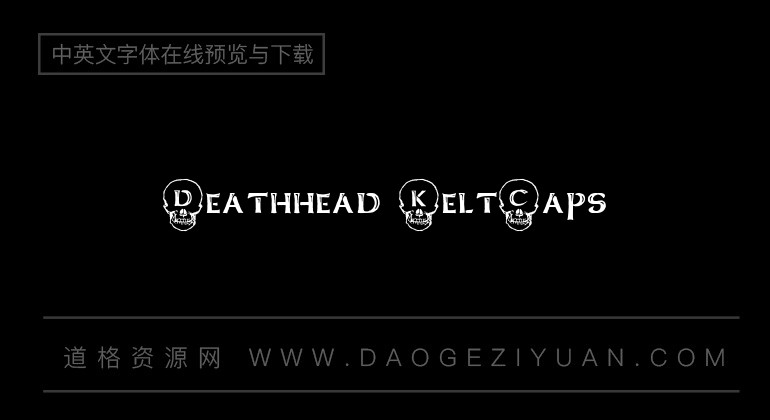
Deathhead KeltCaps
Deathhead KeltCaps 字体是一种基于凯尔特文化元素的装饰性字体。这种字体的特点是字母的轮廓线条粗细不均,有些字母的上方会有尖锐的尖刺,字母之间也存在一定的连接。 Deathhead KeltCaps 字体的风格独特,适合用于设计古代、奇幻、神秘、恐怖等主题的文本。这种字体的使用通常需要注意一些细节,比如避免过多使用,以免过于复杂难以辨认,同时也要注意字母之间的连通问题,以保证整体的美观和可读性。 总的来说,Deathhead KeltCaps 字体是一种非常有特色的装饰性字体,可以用于设计独具特色的文本效果,但需要谨慎使用。
Deathhead KeltCaps是一款非常不错的手写艺术字体,具有很好的视觉感,适合于文化类的宣传设计、商业类品牌的广告和产品包装设计以及个性化文字排版等较多场景。